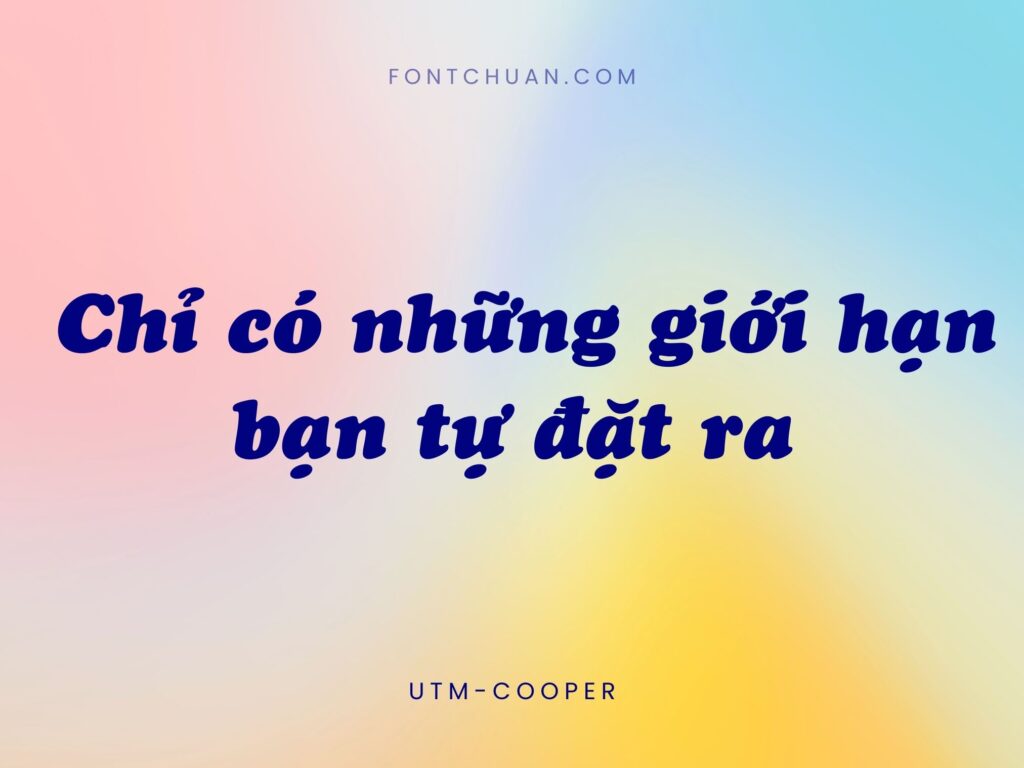
Font UTM Cooper Việt Hóa
UTM Cooper là phiên bản Việt hóa của font chữ Cooper, một kiểu chữ serif đậm được thiết kế bởi Oswald Bruce Cooper và phát hành lần đầu vào năm 1922. Font này nổi bật với các ký tự có đường nét tròn trịa, dày và mềm mại, tạo cảm giác ấm áp và thân thiện. Phiên bản Việt hóa đã được thực hiện bởi Công ty TNHH Vitoen, hỗ trợ đầy đủ tiếng Việt cùng hơn 100 ngôn ngữ khác. Đây là một trong những font được cộng đồng thiết kế sưu tầm và chọn lọc nhằm đáp ứng nhu cầu đa dạng trong thiết kế.
UTM Cooper có cấu trúc chữ với các nét đậm và tròn trịa, tạo nên sự nổi bật và dễ đọc. Font này phù hợp cho các ứng dụng như thiết kế tiêu đề, logo, bao bì sản phẩm và các ấn phẩm in ấn yêu cầu sự thân thiện và gần gũi. Các ngành nghề như quảng cáo, giáo dục, công nghệ và bất động sản có thể tận dụng UTM Cooper để tạo điểm nhấn độc đáo trong thiết kế.